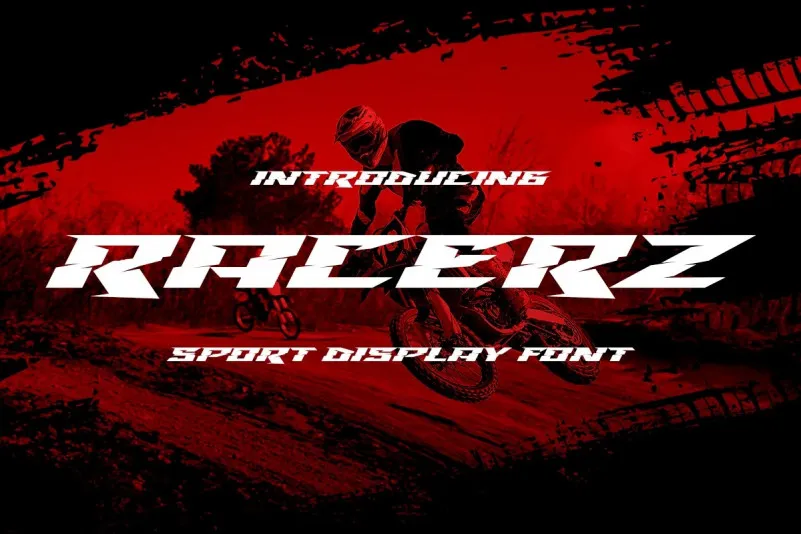
Racerz Font
A Racerz Font é uma fonte Display que apresenta a modernidade e a futurismo num conjunto totalmente caps lock. Ideal para qualquer tipo de projeto visual, ela oferece infinitas possibilidades para títulos, logotipos, tipografia, roupas, revistas, panfletos e embalagens. Esta fonte, criada pela Almarkha Type em um marketplace de design 99designs, é perfeita para aqueles que buscam adicionar uma pegada mais moderna e profissional aos seus projetos. Ela se destaca por sua simplicidade e sofisticação, tornando-a uma opção irresistível para designers em busca de elementos gráficos que elevem seu trabalho a um novo nível. Seja você um designer de moda criativo, um editor de revistas ou um profissional de embalagens, a Racerz Font está aqui para ajudá-lo a criar designs mais modernos e imprimíveis, tornando-se uma ferramenta indispensável na sua carteira de recursos gráficos.